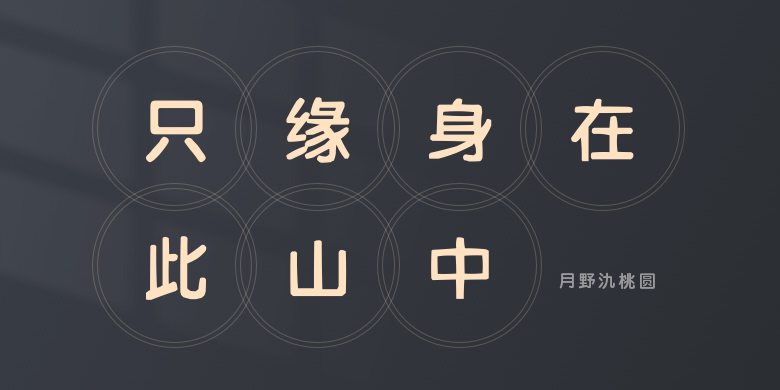
月野氿桃圆
月野氿桃圆,这款字体结构工整、笔画清晰,兼顾美观与易读性,适用于标题、正文、海报、包装、LOGO 等多种场景。字形优雅稳定,风格百搭耐看,适配日常排版与创意设计,让文字呈现更舒适、更具质感。月野氿桃圆一笔一画,皆是细节,以均衡的比例、流畅的线条打造舒适视觉体验,字形端正大气,风格简约现代。无论是商业设计、品牌宣传还是日常排版,都能轻松驾驭,让文字更有格调与力量。月野氿桃圆字体下载。